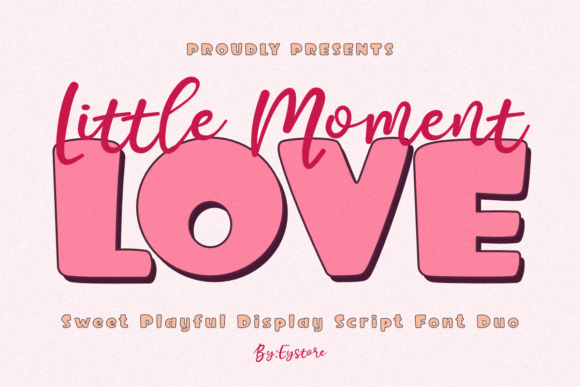
Little Moment Love Duo
適切なデザイン要素を見つけるのは難しい場合がありますが、Little Moment Love Duoは作品を即座に引き立てる優れたコレクションを提供します。
POD(オンデマンド印刷)製品、結婚式の招待状、またはソーシャルメディアのグラフィックを作成している場合でも、Little Moment Love Duoは理想的です。